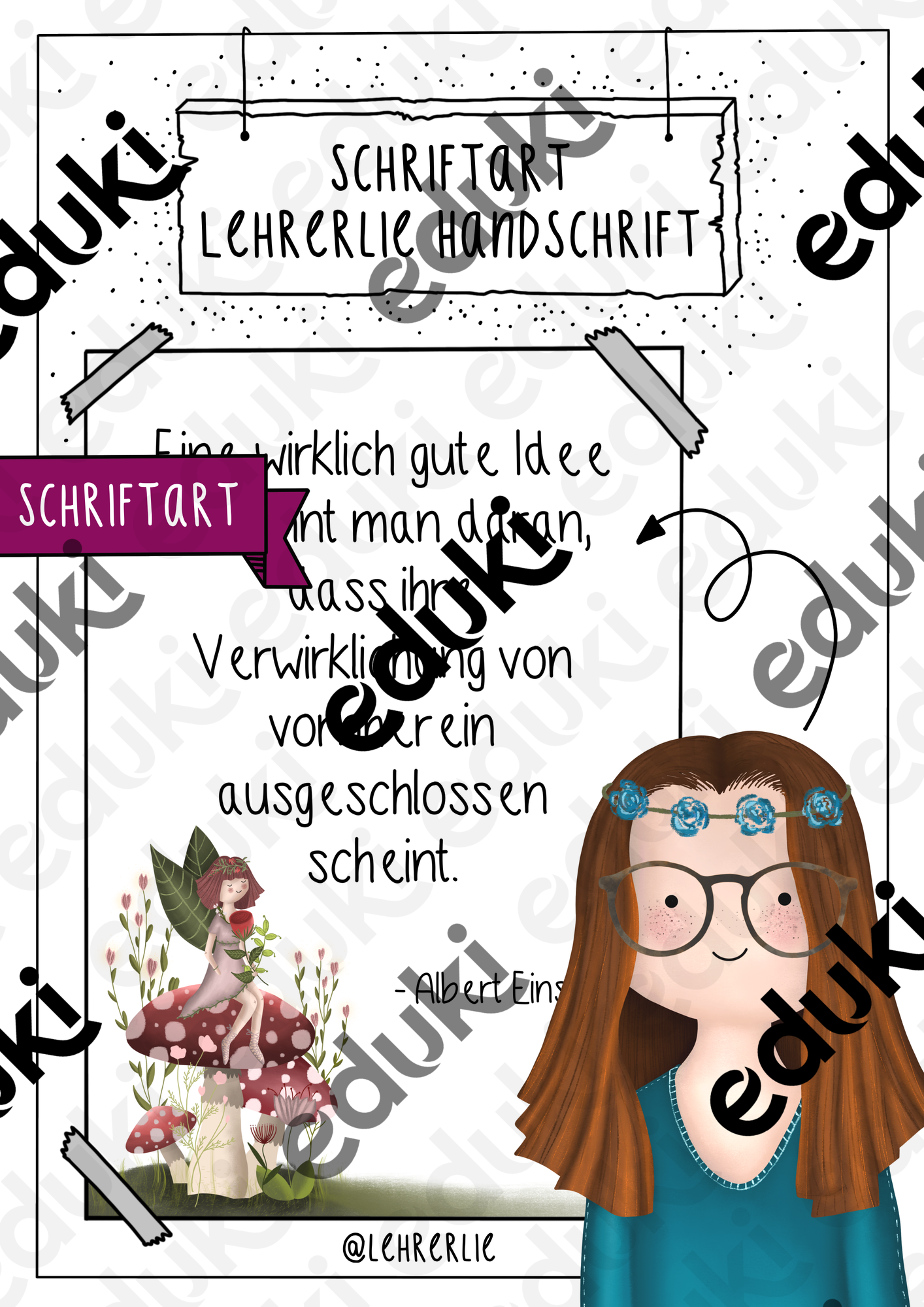
selbst erstellte Schriftarten - Lehrerlie Handschrift - Schriftart - Pinselkomponistin - Deckblatt
Schriftart im Handschrift - Style!
Lehrerlie Handschrift - Schriftart